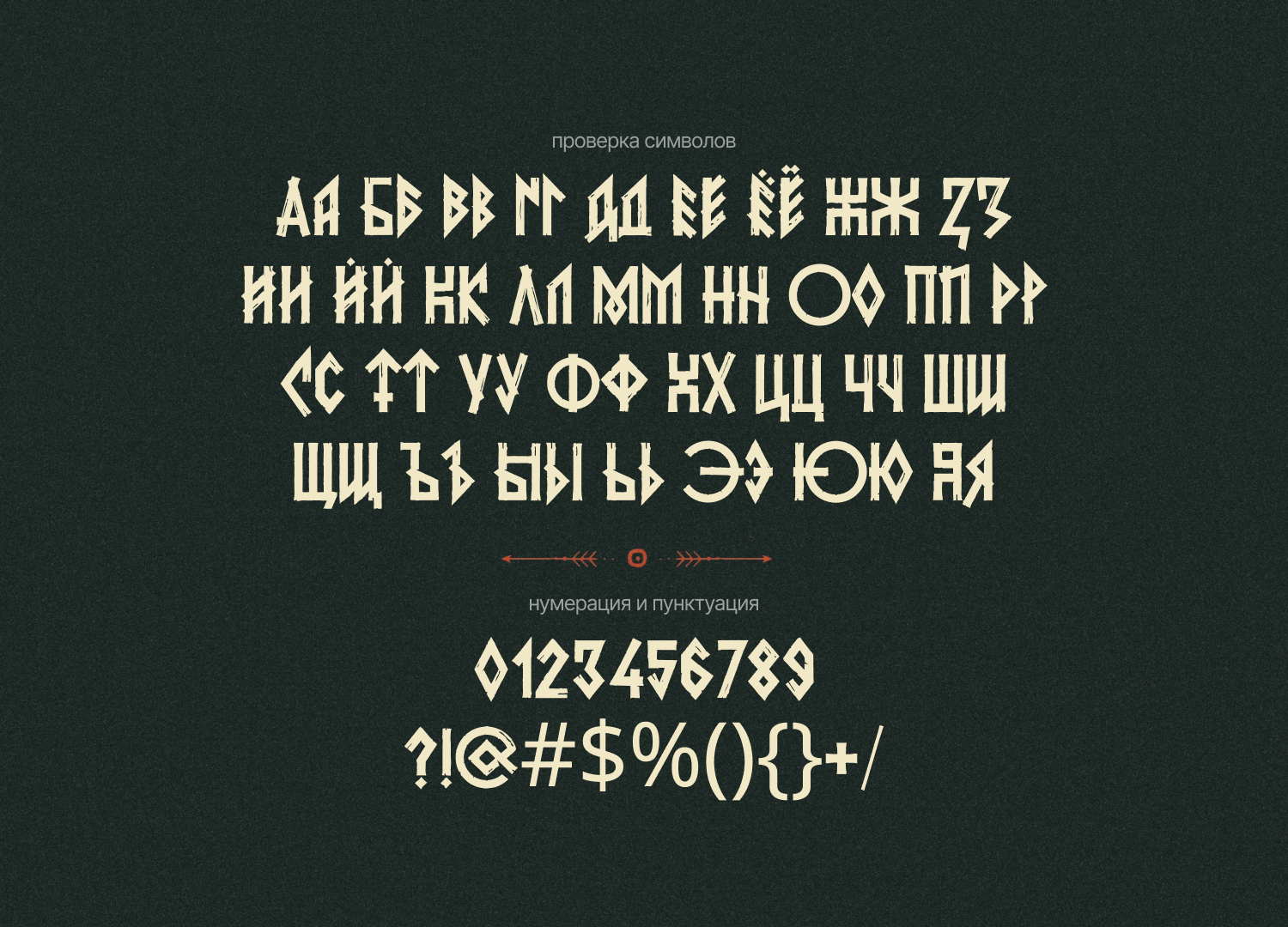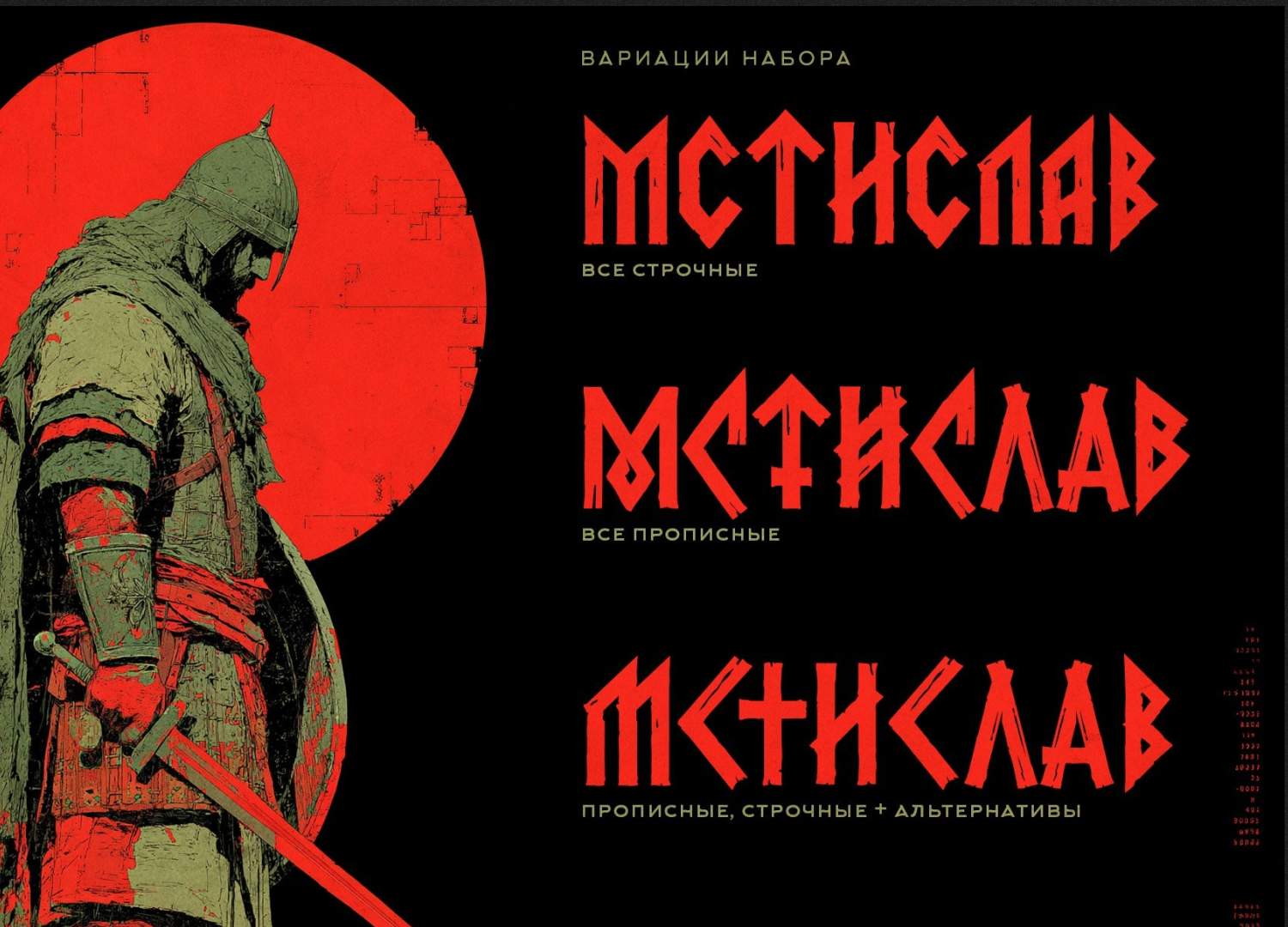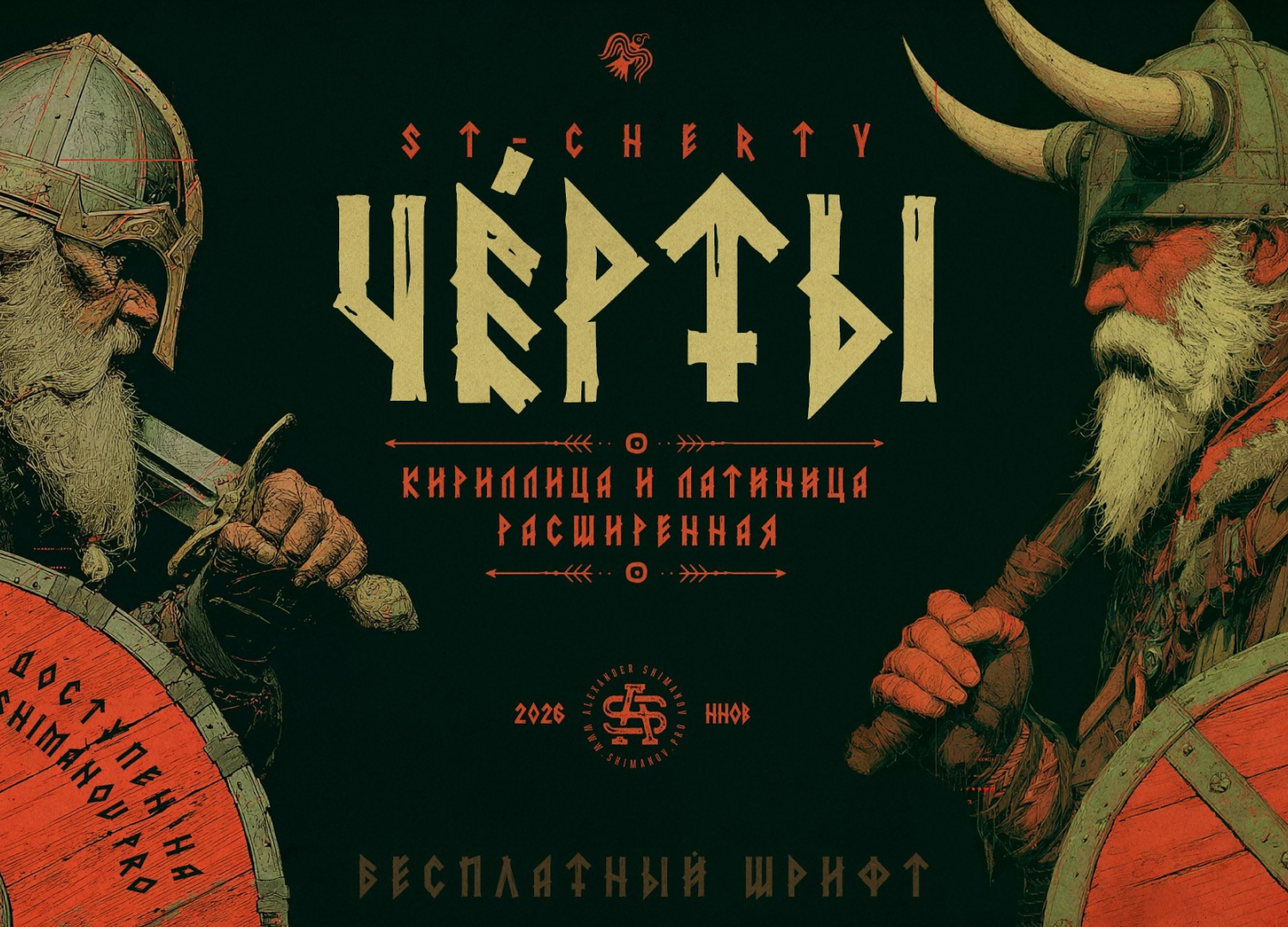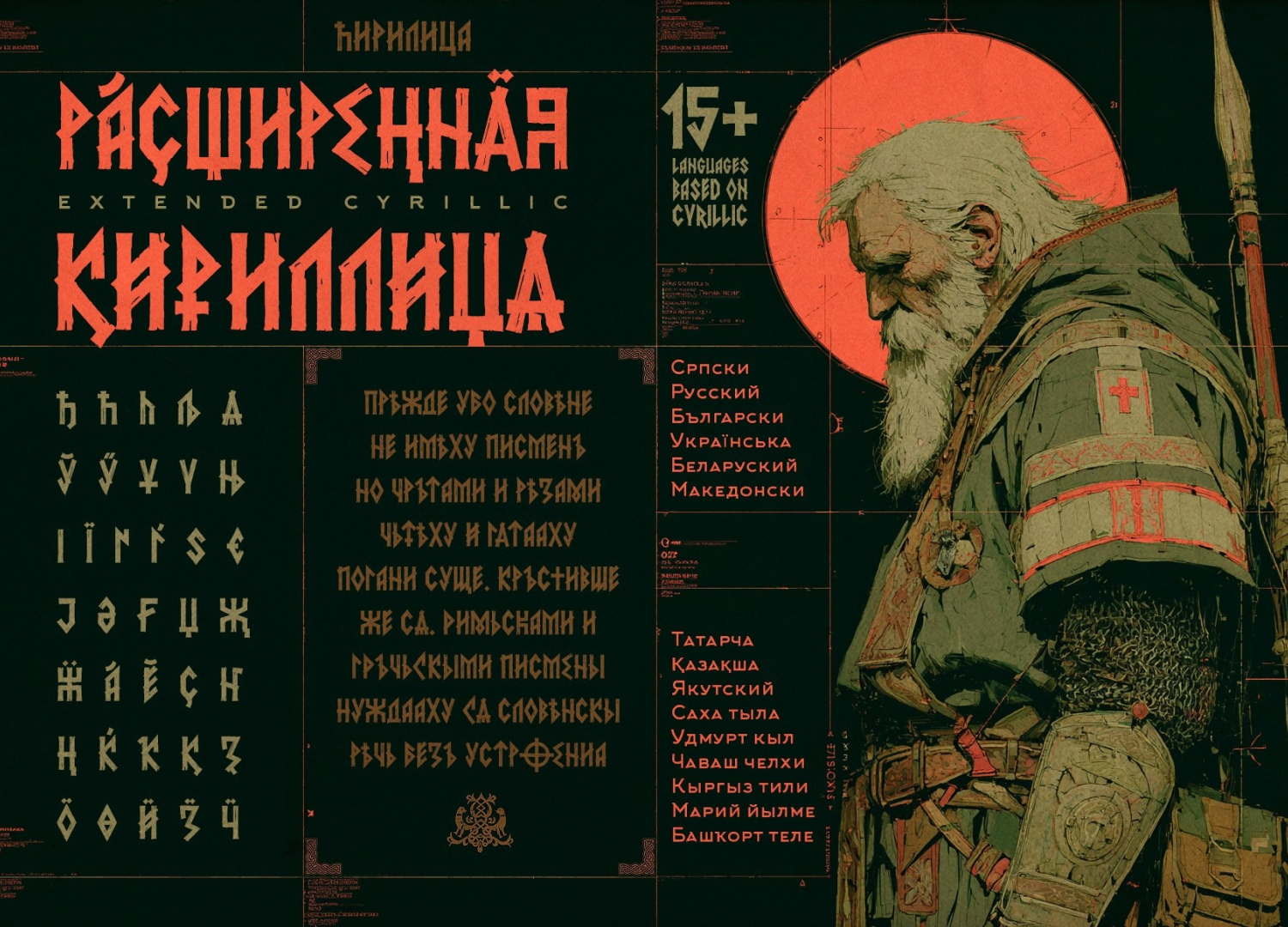
Бесплатный шрифт ST-Cherty (Черты)
Бесплатный шрифт в древнеславянском стиле. Буквы угловатые, напоминают руны, сразу веет стариной и чем-то суровым. Есть кириллица и латиница.Отлично зайдёт для исторических проектов, игр, фолк-тематики, мерча с языческой эстетикой или обложек для металла. Презентация сохранена от автора) Я добавил только 2 слайд для наглядности